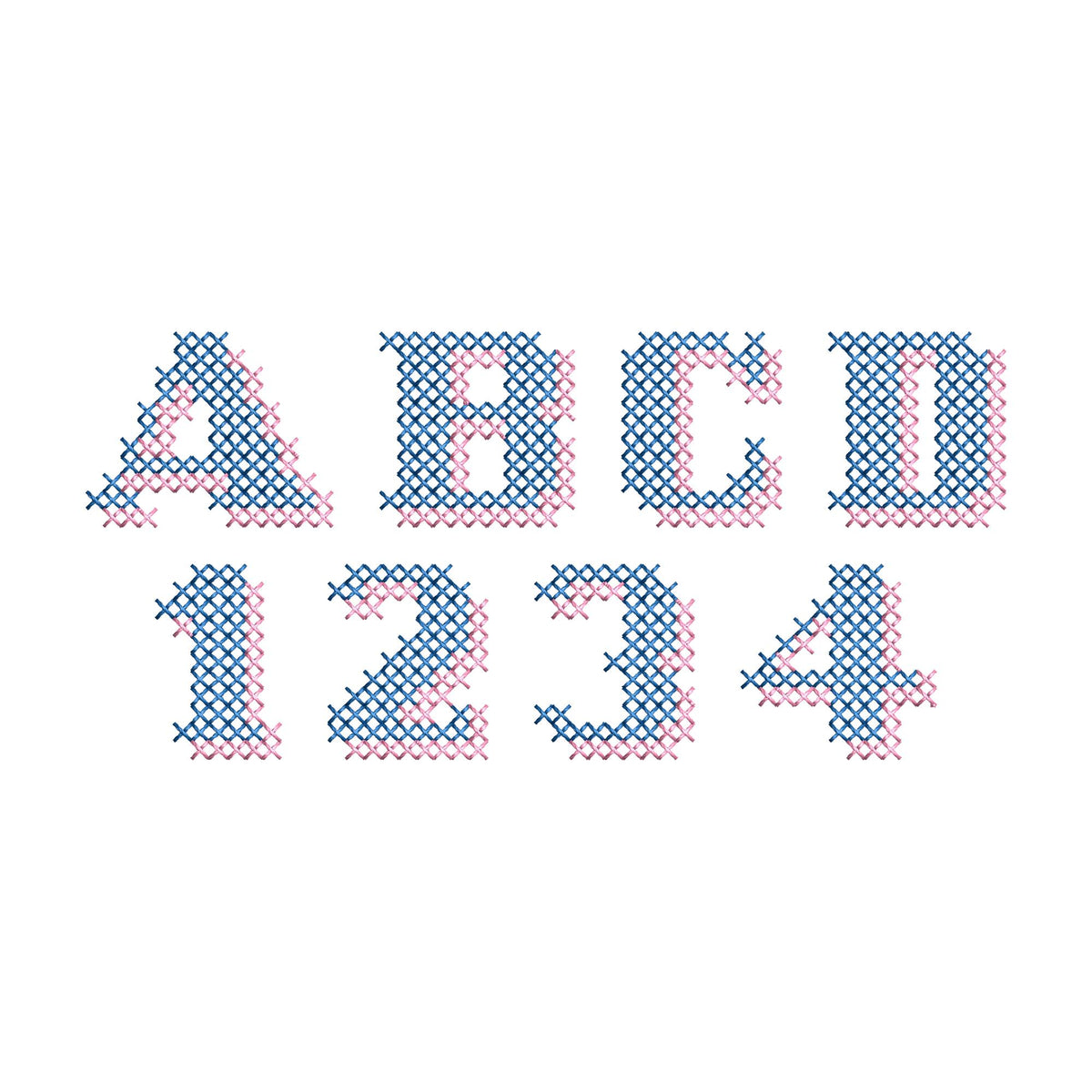
Echte Kreuzstich-Schrift mit Schatten
Eine authentische, kräftige Kreuzstich-Blockschrift mit Schatten im Folk-Stil. Charmant für Namen, Sprüche und Mustertücher.
Die Buchstaben gibt es in vier Mini-Größen: 20, 23, 28 und 36 mm. Kreuzstich-Buchstaben mit weichem Schatten. Mit Großbuchstaben A bis Z, Zahlen 0 bis 9 und den Zeichen ! und ?
- Kreuzstich-Schatten-Blockschrift
- Großbuchstaben A bis Z, Zahlen 0 bis 9, ! ?
- 4 Größen: 20, 23, 28 und 36 mm